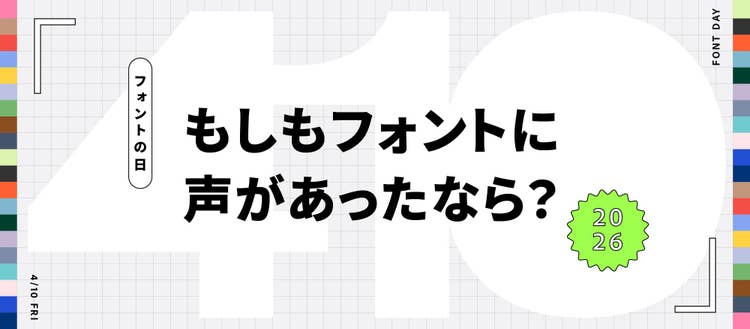
4月10日(金)フォントの日に、
―もしも
フォントから
厳選した
投稿開始は
フォントが
フォントの
また、
フォントの声色紹介
- 凸版文久ゴシック Pr6N R
- 丁寧に
編まれた、 温度の ある 日常語。 耳元で優しく 頷くような声。
- TK-takumiお
気楽 マーカー体 H - 肩の力が
抜けた、 人懐っこい喋り口。 語尾が 跳ねる、 素顔のままの 言葉。
- AH白洲学校ペン楷書体 W12
- 背筋を
伸ばした人が、 一音一音を 慈しむように 紡ぐ、 透き通った 理知でやさしい声。
- FOT-
筑紫明朝 Pr6N L - 澄み切った
ソプラノ。 指先まで 神経が 通った、 湿り気のある囁き。
- ドットのじ
- 規則正しく
刻まれる、 揺らぎある 無機質で 誠実な リズムでの ビープ音。
- ネオクロ バリアブル
- 低く太く響く、
遊び心のあるバス。 力強いのに、 口角が 上がっている 声。
- Moolong チョコレート バリアブル
- 蜂蜜のようにとろける、
低音の 甘い吐息。まどろみの 中の ララバイ。
- 砧 芯 StdN 12K
- 氷細工が
溶けるような 極細の ハイトーン。 吐息に 近い、 純白の 響き。
- ADSひかり
- 木漏れ日の中で紡がれる、
無垢な童歌。心が洗われるような 無垢な発声。
- 貂明朝
アンチック Heavy - 古い書物から
立ち上る、 深く穏やかな語り。 歴史を 背負った、 温厚な低音。
- みぞれ墨東
- 霧雨の
中の低い ハミング。 潤いを 帯びた、 落ち着き払った テノール。
- ロゴライン Std M
- 広場に
響く、 はつらつとした呼びかけ。 拍手が 混じるような 賑やかさ。
- ヒグミン に
じみ - 真夜中の
さざめき。か細いけれど、 芯が 震えるような 独創的な旋律。
- VDL 黒明朝 M
- 銀細工が
触れ合うような 硬質な高音。凛とした、 涼やかな 独白。
- TAw-
竹田城跡 - 山の空気を
切り裂くような、 野太い 雄叫び。 骨太な、 土の匂いのする主張。
- かづらき
- 筆先が
紙を 打つ音まで 聞こえる、 鋭い謡 (うたい)。気品に 満ちた 静寂の 響き。
- 貂明朝 Regular
- 妖精が
笑うような、 丸みのある滑らかな声。 どこか懐かしい、 誘うような 響き。
- SicハンディックH Regular
- 蓄音機から
流れる、 弾むような 蓄声。 鼻歌を 歌うような 軽快さ。
- ヒラギノ角ゴ ProN W6
- 重心に
揺るぎがない、 明瞭な宣告。 一語一語を 置くような 信頼の 響き。
- DNP 秀英初号明朝 Std
- 腹底から
響く、 艶やかな バリトン。 包容力の ある豊かな 余韻。